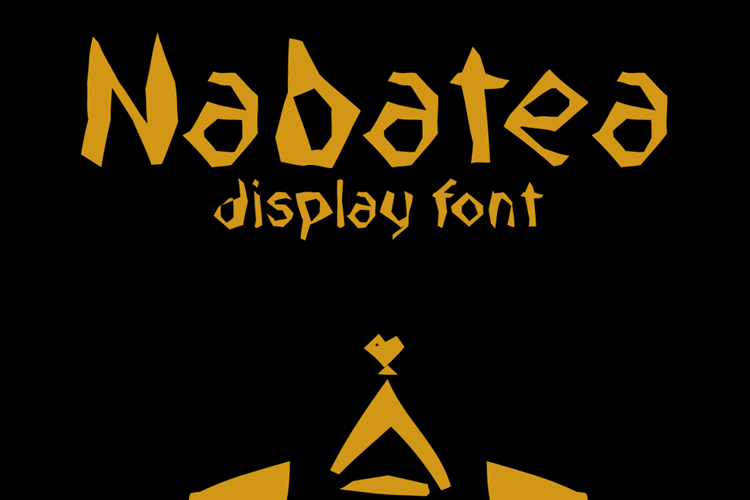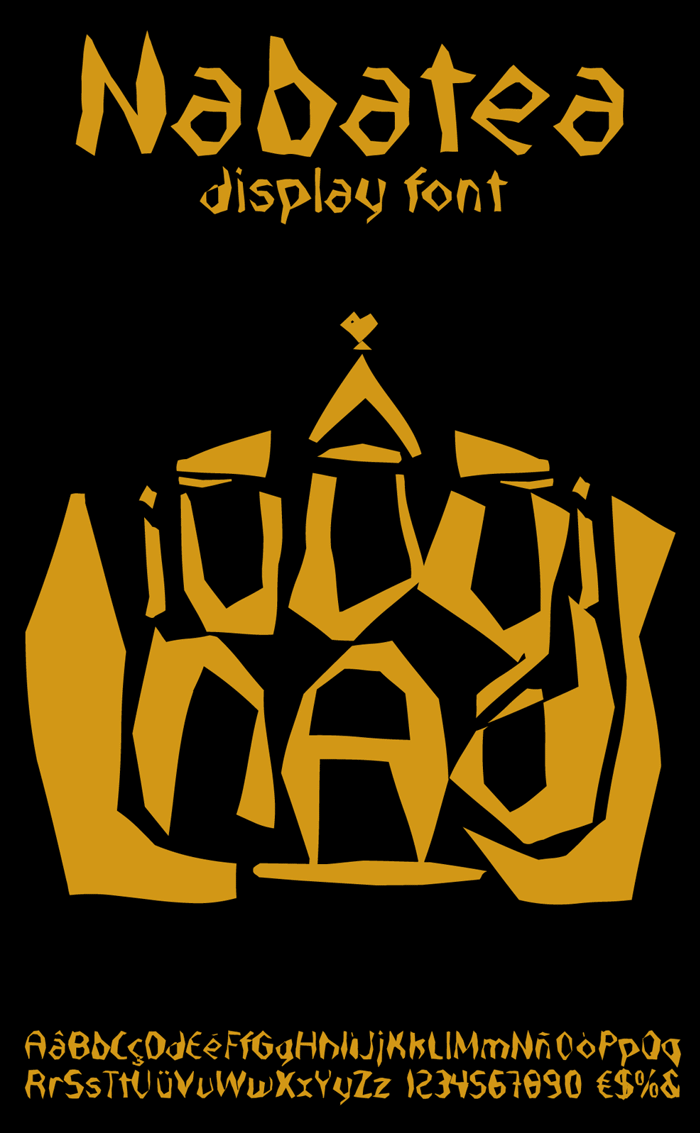
Nabatea Font
Nabatea es la letra diseñada a golpe de mazo, sobre la dura piedra, por el individuo de un antiguo pueblo de la Arabia Pétrea, entre el mar Rojo y el río Éufrates. La tipografía es un homenaje a Petra, capital nabatea.